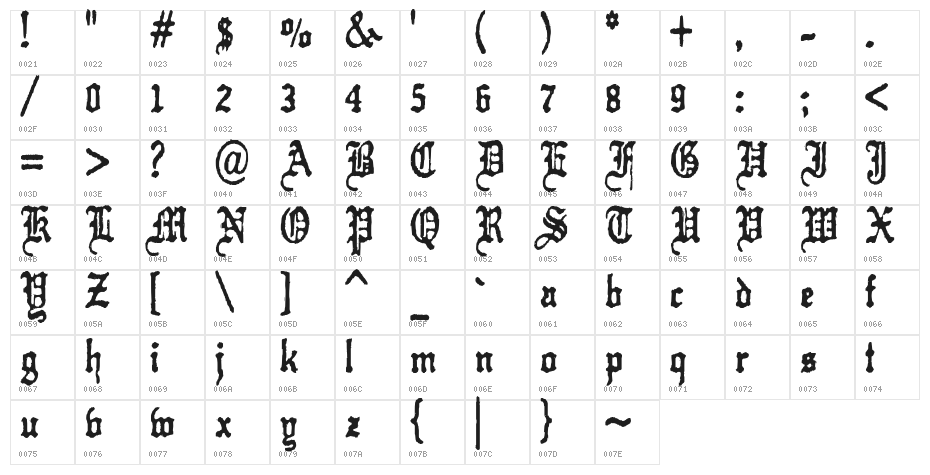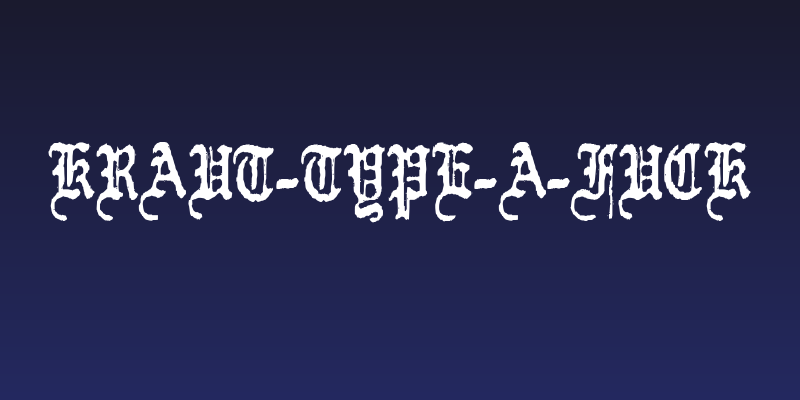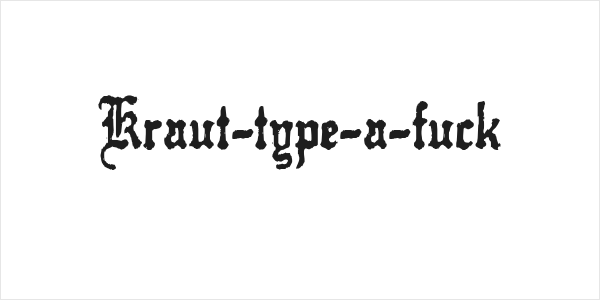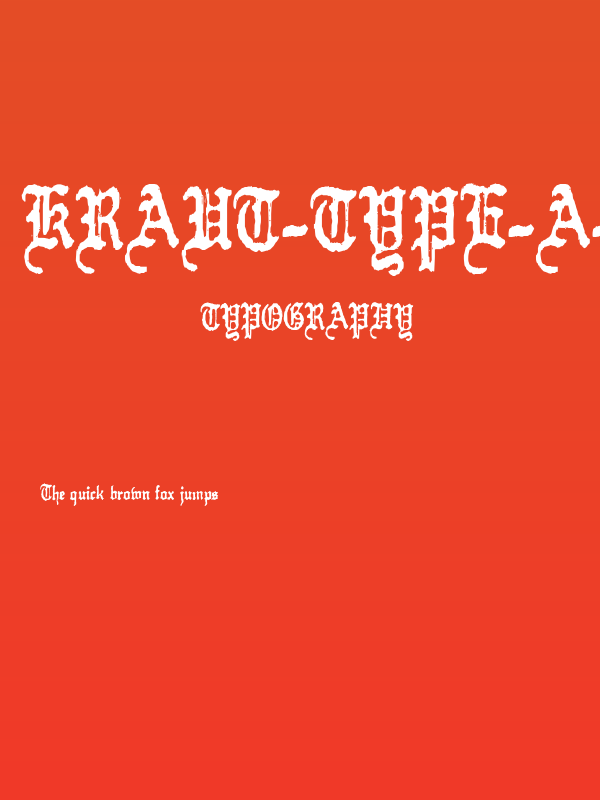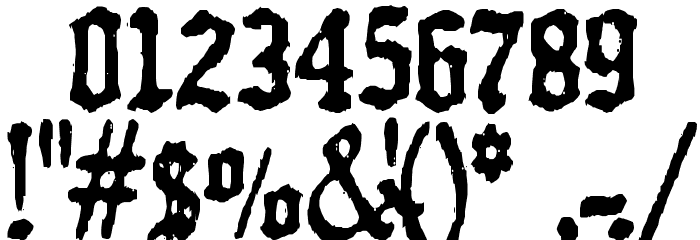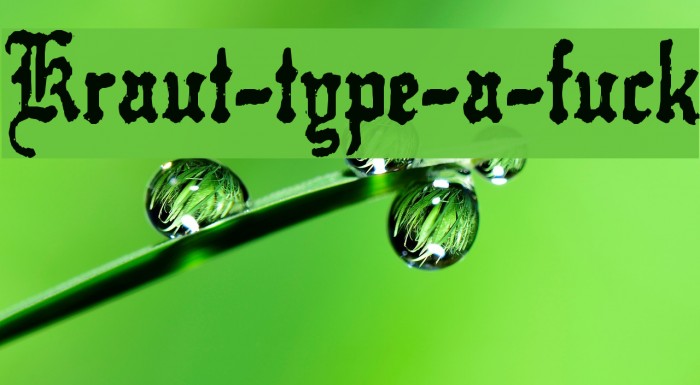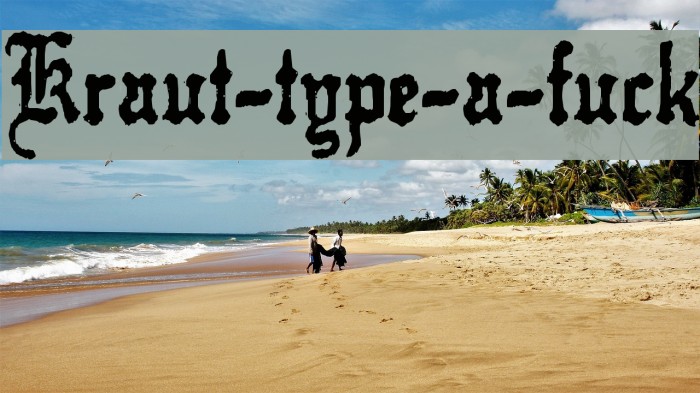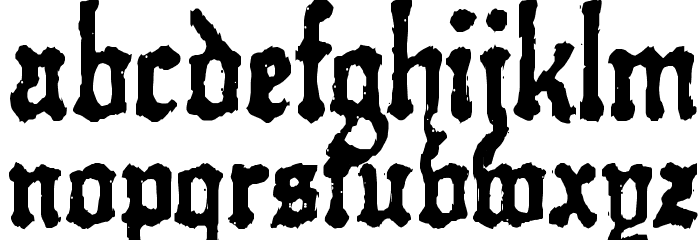
Kraut-type-a-fuck Font
✎ Gothic
| Kategorien | Gothic |
| Gesamtstil | Vintage |
| Anwendungsfall | Logos, Headlines, Decorative purposes |
| Vorgeschlagene Projekte | Ideal for use in vintage-themed designs, tattoo art, gothic literature covers, and branding for luxury products. |